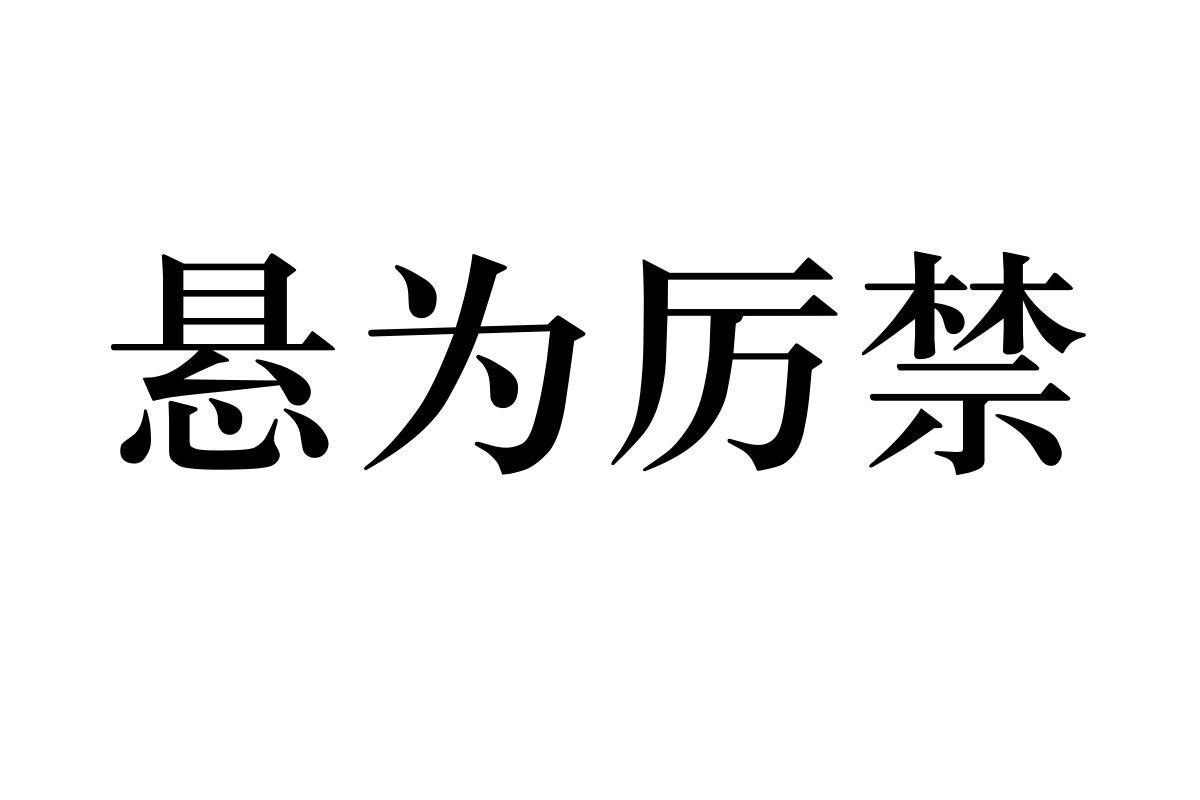
汉仪中宋简字体,是汉仪公司推出的一款免费商用字体。这款字体以宋代的书法风格为基础,线条流畅,结构严谨,具有很高的艺术价值和实用性。
汉仪中宋简字体的特点如下:
1. 字形优美:汉仪中宋简字体的笔画粗细适中,线条流畅,给人一种优美的视觉效果。
2. 结构严谨:字体的结构严谨,每个笔画都经过精心设计,使得整个字体看起来非常和谐。
4. 适用于多种场景:汉仪中宋简字体适用于各种印刷品、广告设计、网站设计等多种场景,具有很强的适用性。
总的来说,汉仪中宋简字体是一款非常优秀的免费商用字体,适合广大设计师和用户使用。